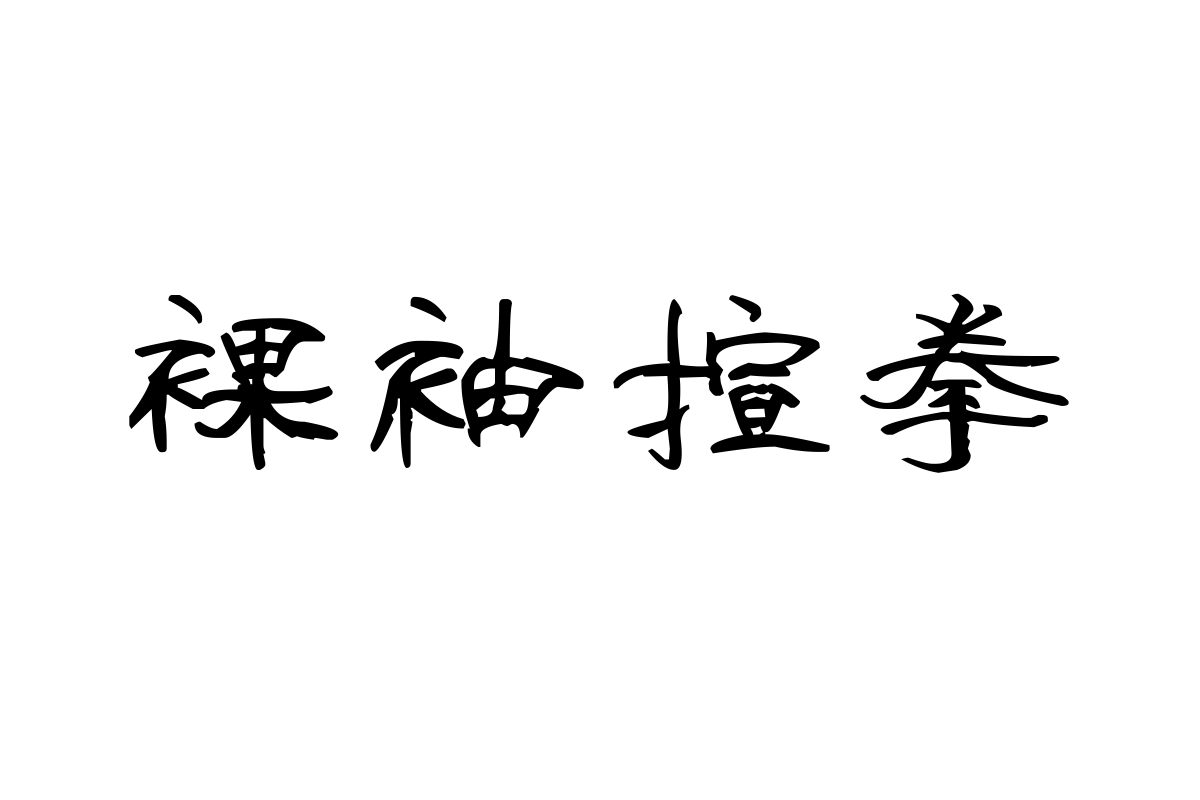
汉标热恋体是一种中文字体,由汉标公司设计。这种字体以其独特的风格和视觉效果而受到许多设计师的喜爱。
汉标热恋体的特点包括:
– 字体结构紧凑,笔画流畅,给人一种轻盈的感觉。
– 字体大小适中,适合用于各种场合的文本展示。
– 字体颜色鲜艳,易于在视觉上吸引人们的注意力。
– 字体样式多样,可以根据不同的设计需求进行选择。
总的来说,汉标热恋体是一款非常实用的中文字体,无论是用于网页设计、平面设计还是其他需要文字展示的场景,都是不错的选择。